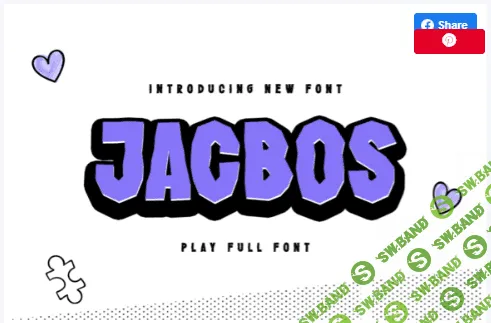
Название: Jacbos Font (2021)
[creativefabrica] Jacbos Font (2021)
Jacbos - геометрический шрифт с толстыми буквами. Этот шрифт идеально подходит для написания веб-дизайнов, визиток и всего остального, что требует смелого подхода.